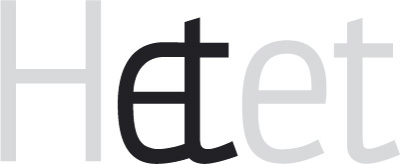
Ist so ein &-Zeichen erlaubt?
Mal ganz davon abgesehen, daß es auf den ersten Blick etwas ungewöhnlich aussieht, frage ich mich, ob es vielleicht überhaupt erlaubt ist, ein &-Zeichen aus einem ganz herkömmlichen "e" und "t" zu formen. Ich habe meinen Tschichold (wg. Ampersand u.s.w.) gelesen – und dabei gelernt: es ist historisch unmöglich, das &-Zeichen auf eine bestimmte Kombination festzulegen. Versalien und/oder Minuskeln? Niemand weiß was Genaueres.
Kann man dann sowas machen? Oder sieht's zu schlimm aus? Kritik erwünscht.
Jan Tschichold ist – so begnadet er gewesen sein mag – auch im Kontext seiner Zeit zu sehen. Wenn ich das richtig beobachtet habe, ist die Kombination aus e und t für das et-Zeichen (unter diesem Namen kenne ich es, oder „kaufmännisches Und“) eher jüngeren Datums, die Rotis etwa verwendet es.
Was spräche dagegen, sich heute auch ein klein wenig vom Altmeister fortzubewegen und es so zu machen, wie Du schriebst? Er wird sich deshalb nicht im Grabe umdrehen.
grundsätzlich ist es kein Problem. Schau Dir mal Tschicholds „Formenwandlung des Et-Zeichens“ an; Da (und z.B. auch in einer Thesis, die sehr viele Variationen beinhaltet) siehst Du, daß dieses Zeichen immer schon die Kreativität der Schriftgestalter angeregt hat!